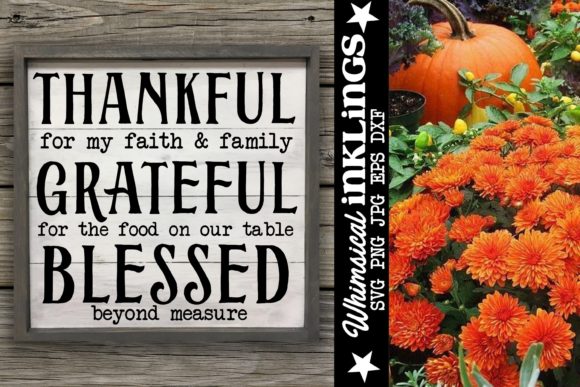
Thankful Grateful Blessed
Nếu bạn đang tìm kiếm các tài nguyên chất lượng cao như Thankful Grateful Blessed, gói cao cấp này là một lựa chọn tuyệt vời cho các dự án sáng tạo của bạn.
Cho dù bạn đang tạo sản phẩm POD (In theo yêu cầu), thiệp mời đám cưới hay đồ họa mạng xã hội, Thankful Grateful Blessed đều là một sự lựa chọn lý tưởng.